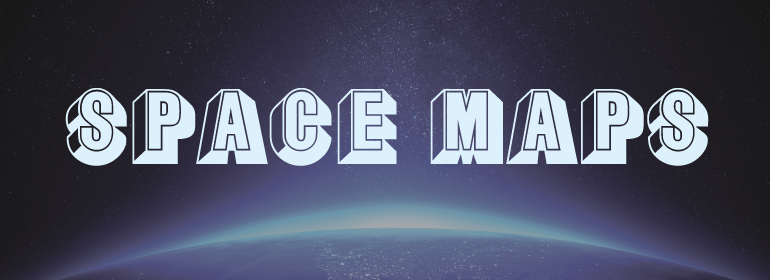
Buxom
Buxom,这款字体结构工整、笔画清晰,兼顾美观与易读性,适用于标题、正文、海报、包装、LOGO 等多种场景。字形优雅稳定,风格百搭耐看,适配日常排版与创意设计,让文字呈现更舒适、更具质感。Buxom一笔一画,皆是细节,以均衡的比例、流畅的线条打造舒适视觉体验,字形端正大气,风格简约现代。无论是商业设计、品牌宣传还是日常排版,都能轻松驾驭,让文字更有格调与力量。Buxom字体下载。
字体品牌: ITC(Monotype) 设计师:Trogman,Robert 字体分类:衬线体 字体属性:外文 字符集:Unicode 发布时间: 2018